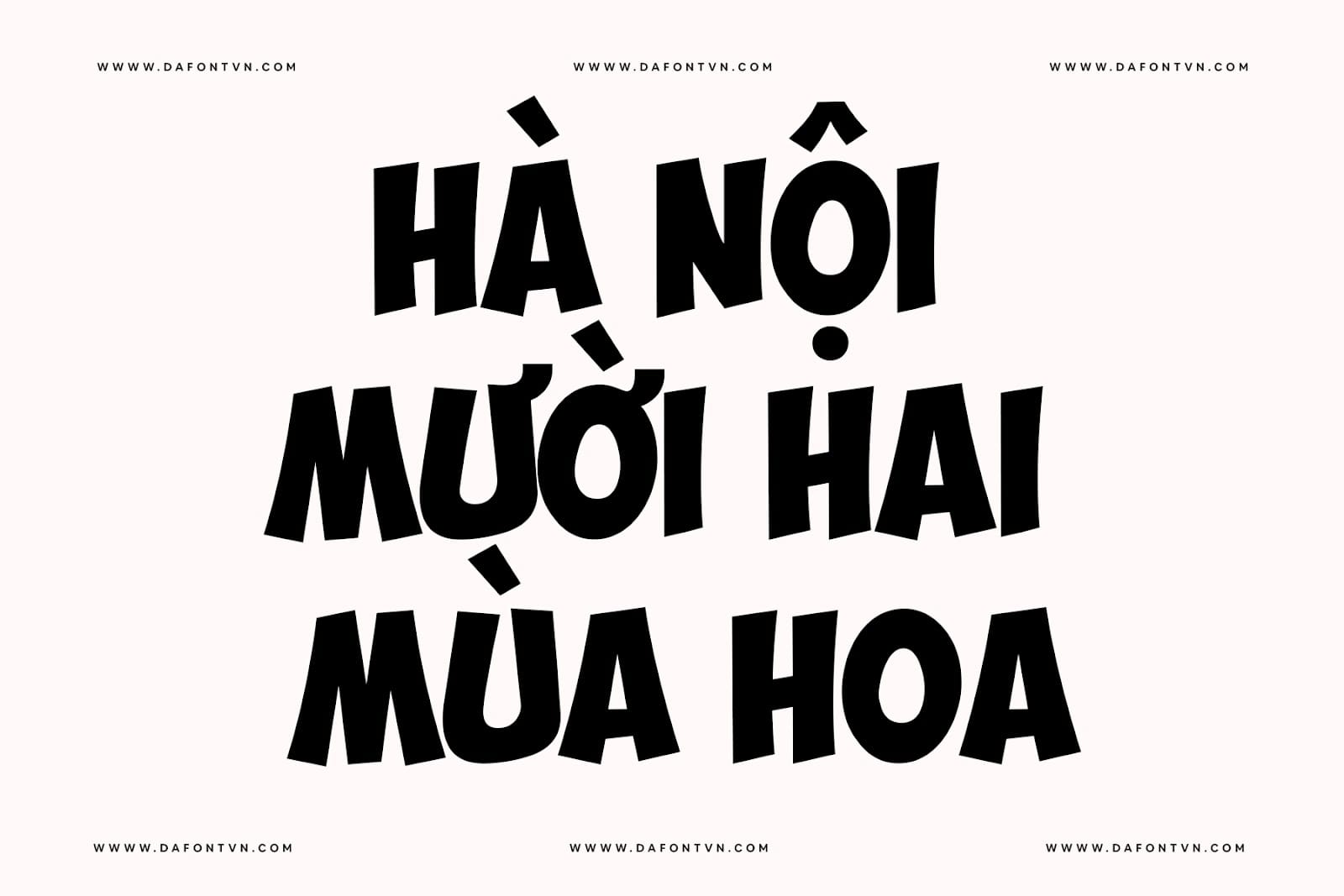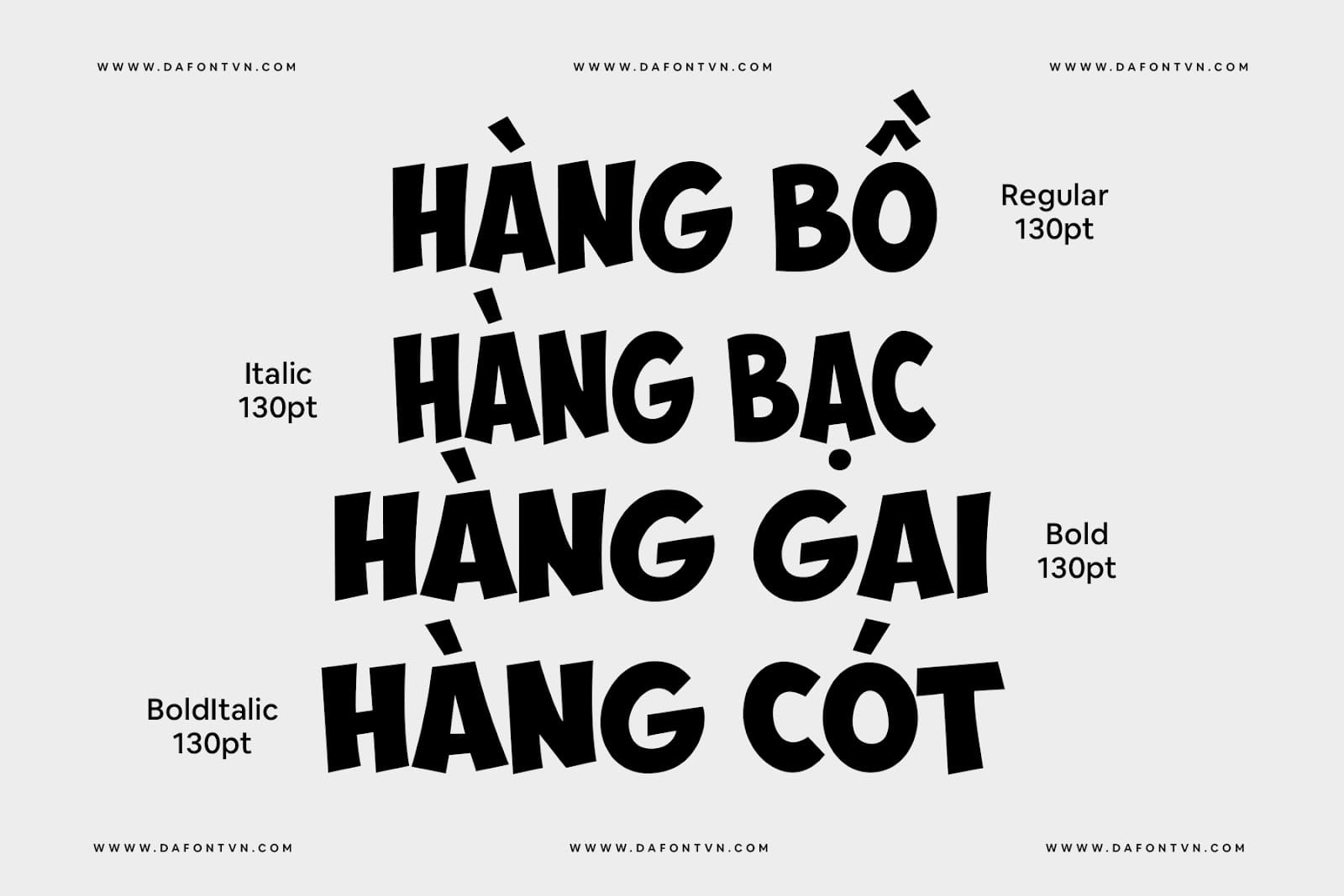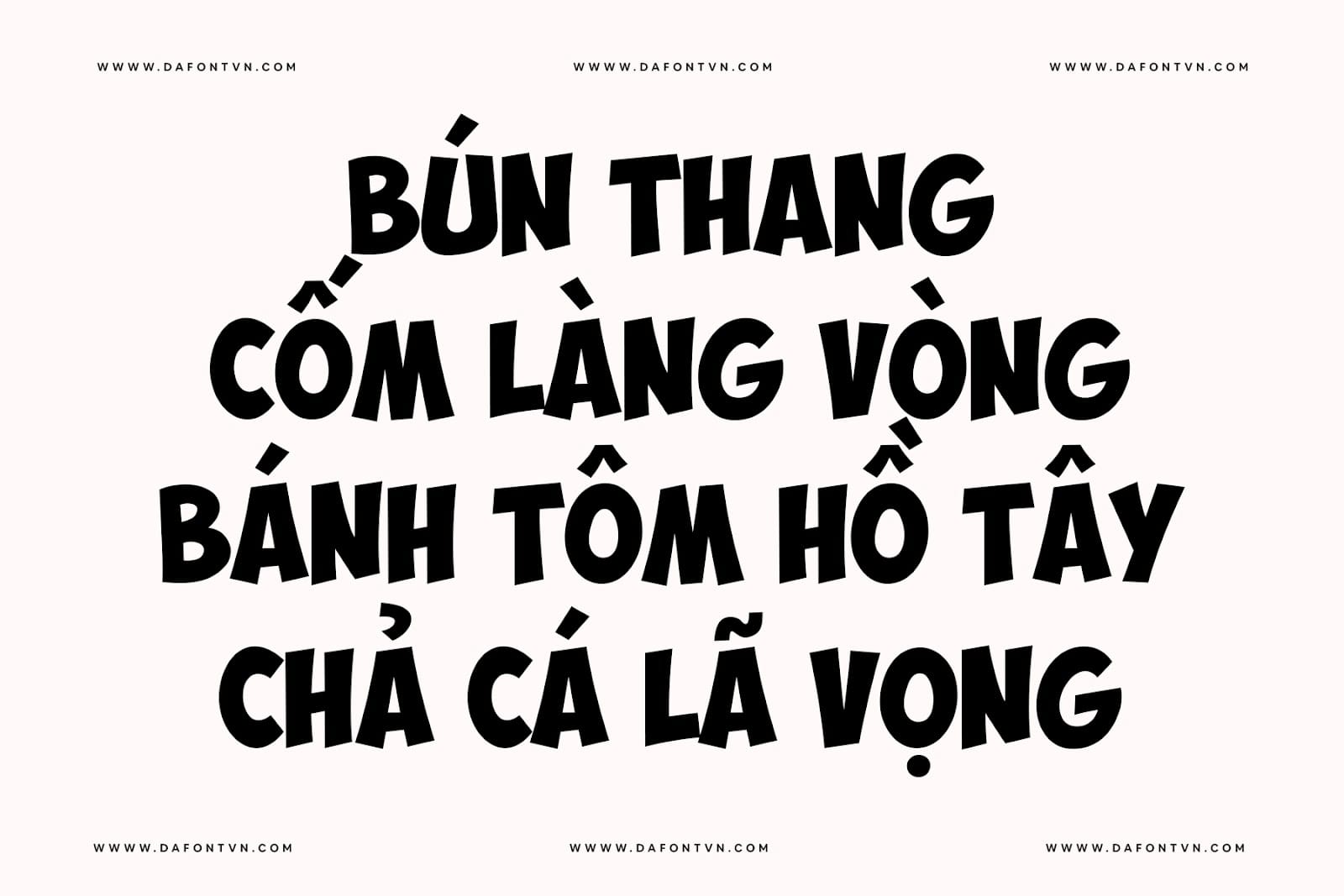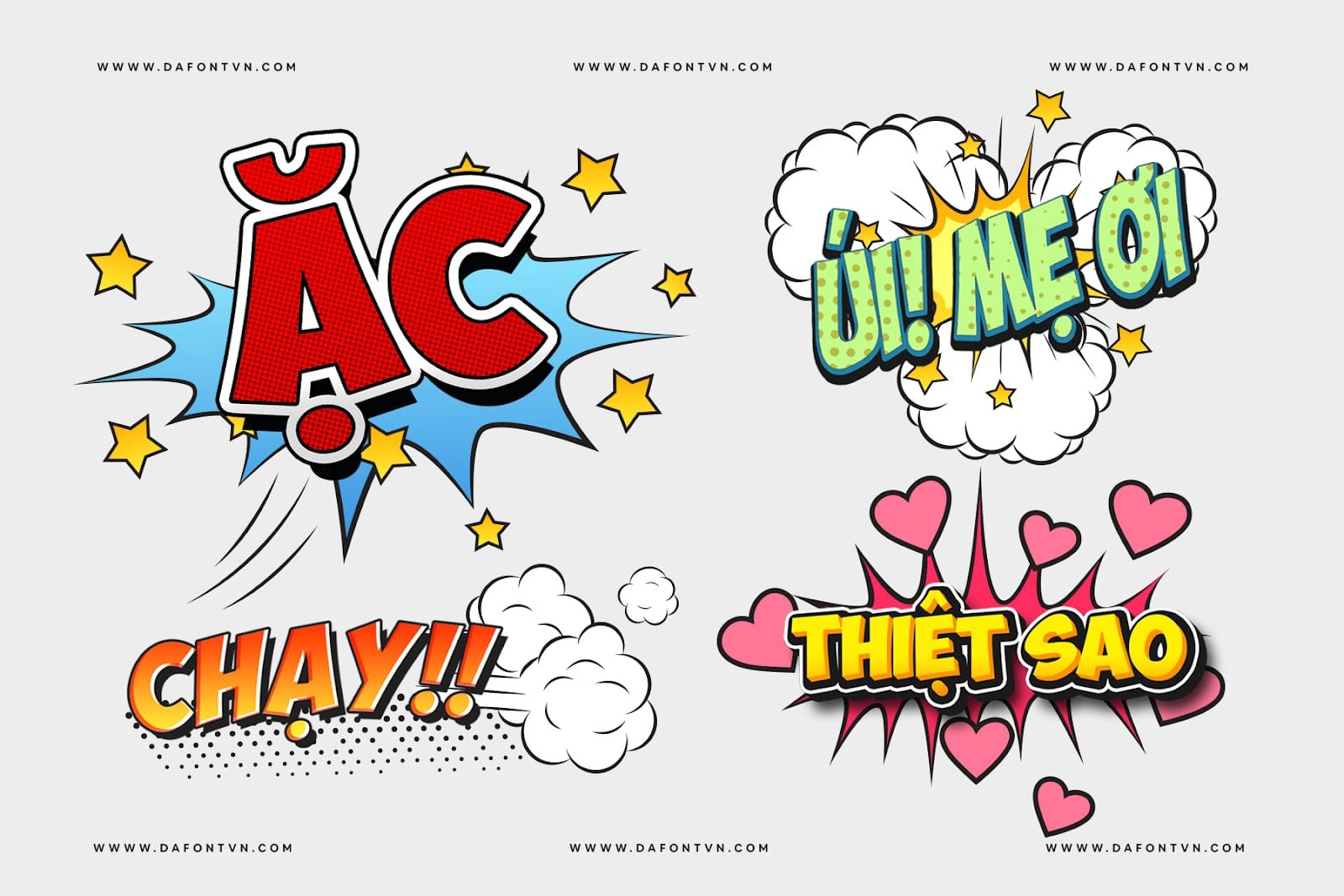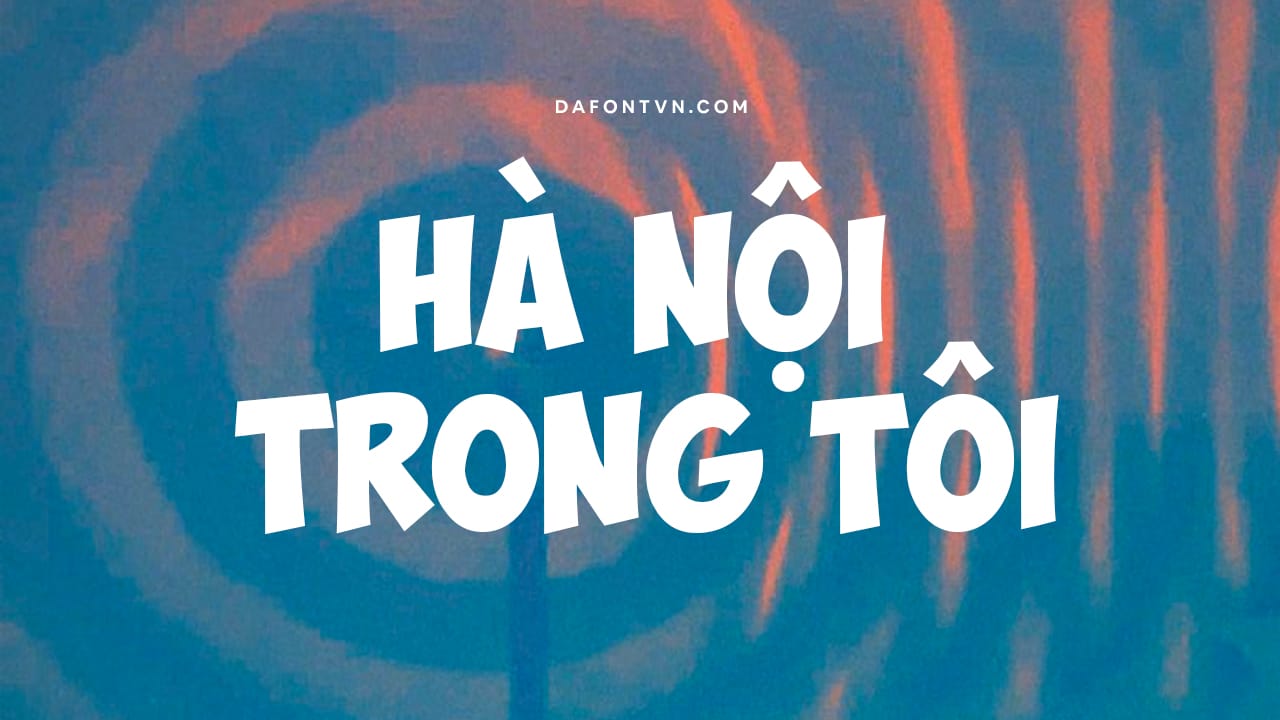
Bạn đang tìm cách nâng tầm thiết kế của mình bằng một chút hài hước và vui tươi? Không đâu khác ngoài Obelix Pro Font, một phông chữ truyện tranh được tạo ra bởi nhà thiết kế Valentin Antonov.
Một trong những tính năng nổi bật của Obelix Pro là chất lượng hoàn hảo. Với từng chi tiết, độ cong độc đáo và trông rất nhịp điệu khiến nó trở nên khác biệt so với các font chữ còn lại, nó có thể được nhận biết dễ dàng và rất dễ đọc.
Obelix Pro cho phép bạn tạo nội dung hấp dẫn về mặt hình ảnh, các nét chữ đậm, hiển thị tốt. Phông chữ này cho phép bạn thỏa sức sáng tạo và biến văn bản thông thường thành những thiết kế sống động.
Không chỉ gói gọn trong việc sử dụng cho phông chữ truyện tranh, Obelix Pro còn có thể sử dụng cho rất nhiều các thiết kế khác nhau từ thiệp mời, poster, tiêu đề, quảng cáo, bao bì sản phẩm cho đến bất kỳ thiết kế nào cần 1 kiểu font hiển thị tốt, dễ đọc và đẹp mắt.
Obelix Pro bao gồm 4 kiểu, font chữ được việt hóa theo yêu cầu, các dấu được thiết kế mới hoàn toàn cho phù hợp với kiểu font này, ngoài ra được kerning đầy đủ và 1 số ký tự được chỉnh sửa lại để tối ưu hơn. Nếu bạn cần việt hóa font nào có thể để lại yêu cầu việt hóa